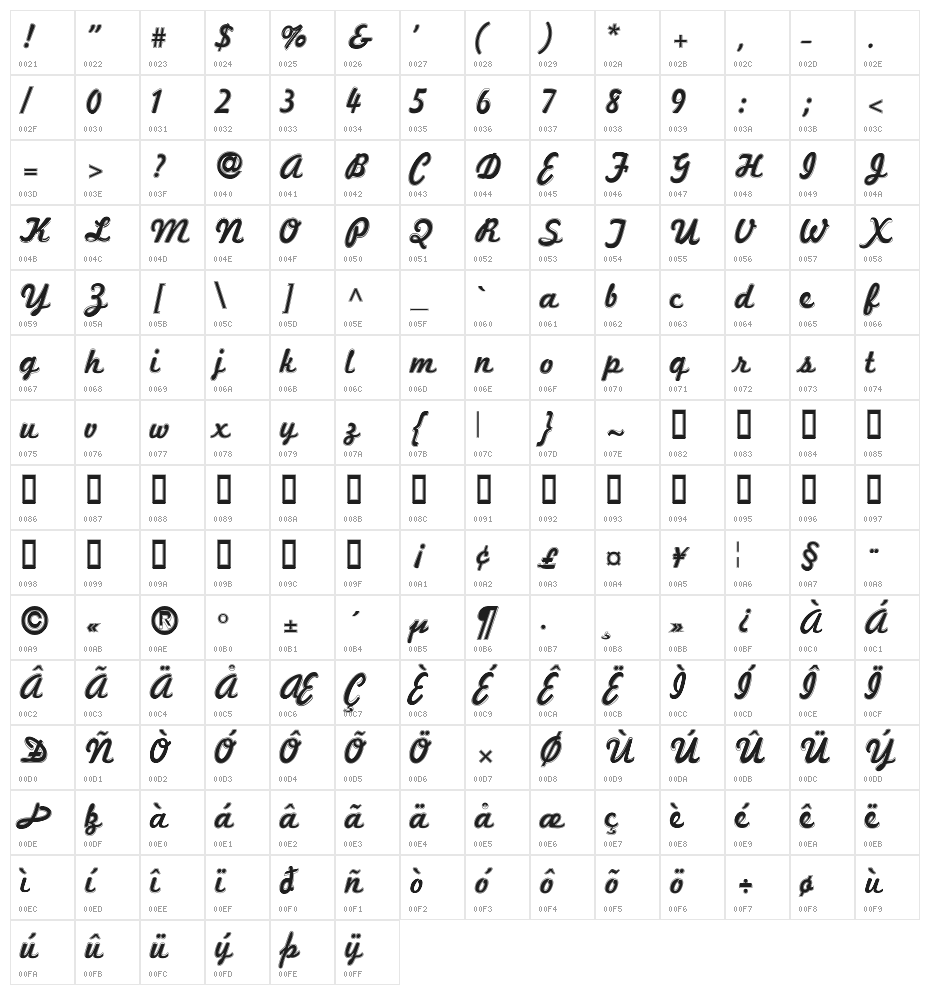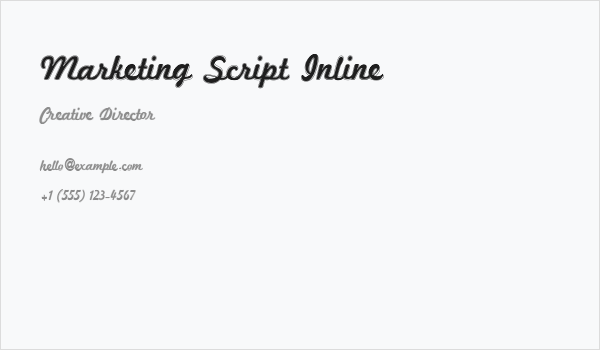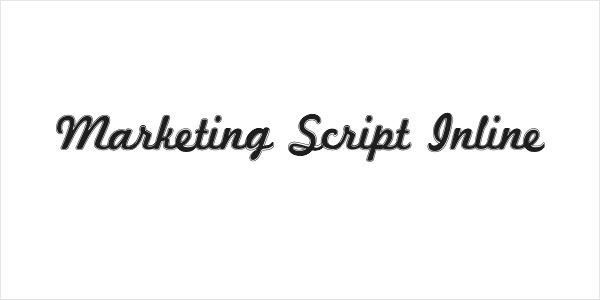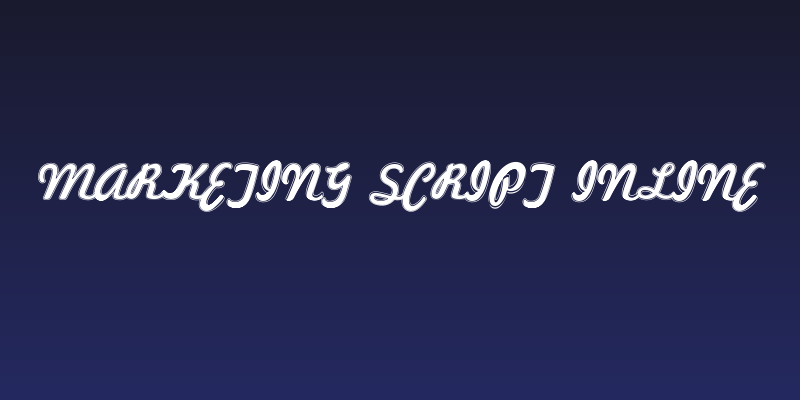
Marketing Script Inline Font
Acest font include 213 caractere. Clic pe orice caracter pentru detalii.
| Caz de utilizare | Logos, Invitations, Branding |
| Proiecte propuse | Ideal for wedding invitations, greeting cards, branding, and logo design where a personal and elegant touch is desired. |